文字具有传递信息快的特点,通过:颜色、形状、色彩、质感等方式,将要表达的信息传达给人,让人识别、记忆并产生影响。通过字体来进行视觉上的形态认识,同时又能够通过将字体图形化、意象化,以更富创意的形式和美学效果准确的表达出作者深层的设计思想。在做设计时你是否总是因为找不到合适的字体而烦恼,想要一款高逼格的字体来进行创作呢?来看看下面这些字体图片中小编为大家推荐的字体吧!
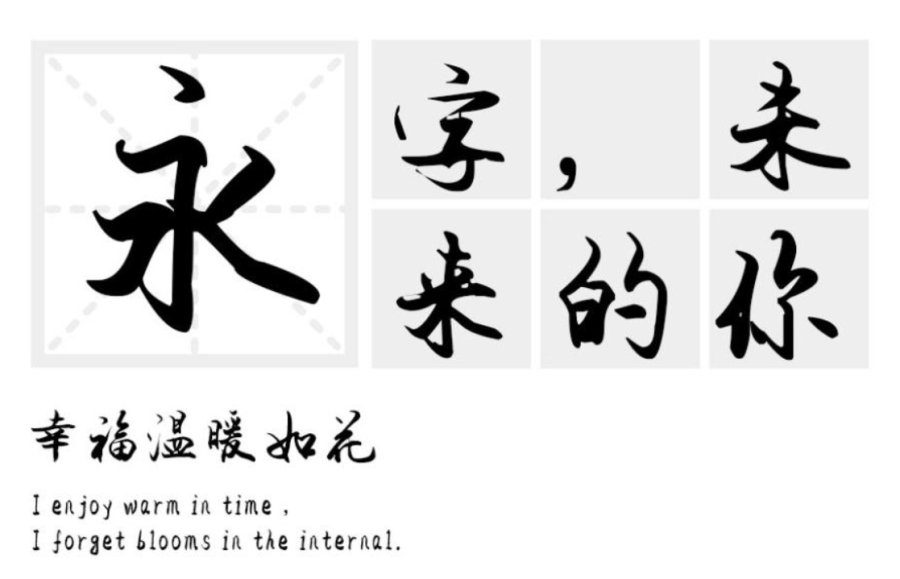
这款“汉标转运体”字体笔画流畅飞扬繁简结合,结体左紧右松,开合对比强烈,进一步强化了动感。整套字体有如一气呵成,行笔迅捷华丽,其个性浪漫洒脱,适用于现代诗歌、短文的排版,以及文化、商业类品牌的广告语设计。
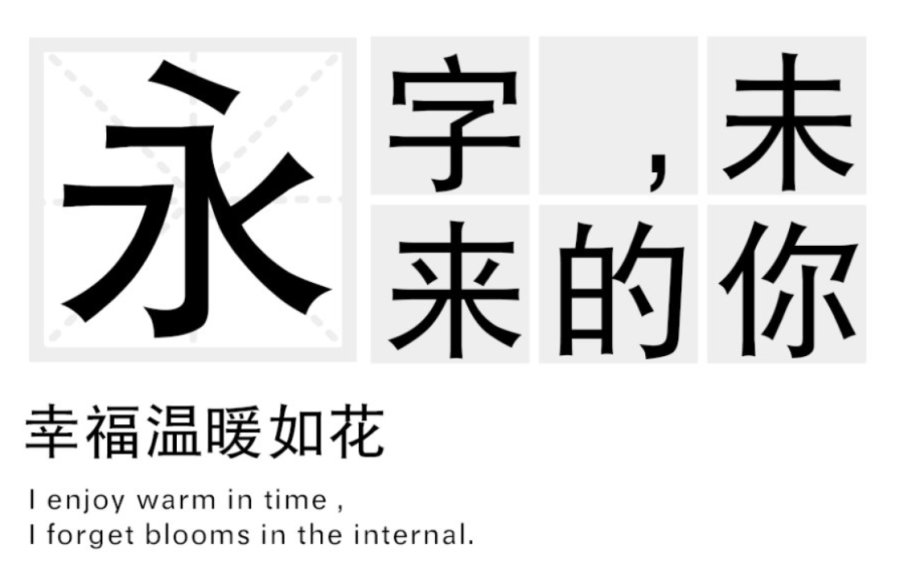
印研所黑一体:这款字体字体源于上海印刷技术研究所1962年完成的专为排印新中国首部《辞海》书眉标题设计的“黑体一号”原稿。字体结构整体方正笔形纤细,字形方中带长,笔形渗入了我国汉字传统书写味,黑白匀称,行款整齐,为了弥补因笔划纤细带来的黑体字不够端庄,在横、直笔划等的起笔和收笔部分略为加重,形似喇叭口的装饰,借以增加端庄、稳定感。
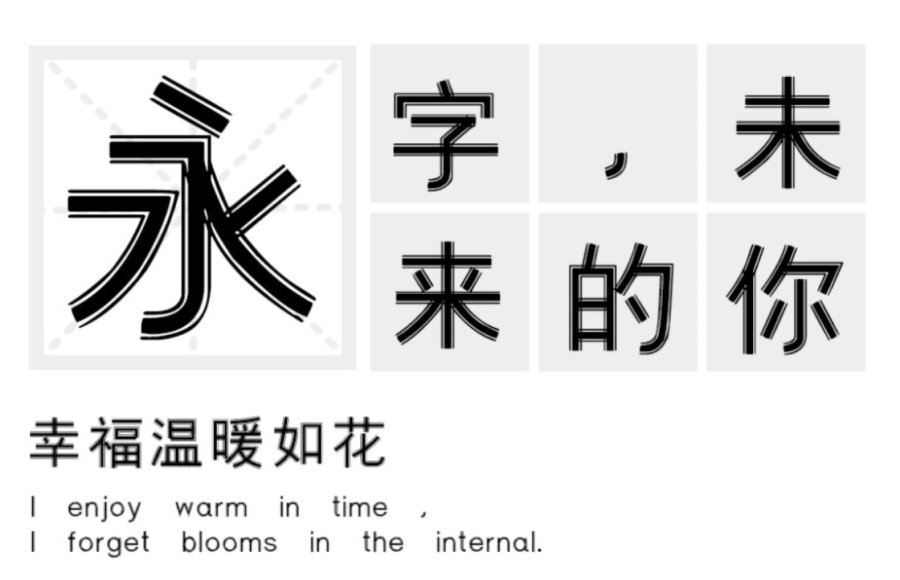
汉标外线黑体:黑字形外部加了细线,正方笔形简练,风格简静优雅;追求远距离读取功能,笔画清晰、易于识别。可标题和正文排版,尤其适合应用在空间导视、品牌形象、包装、广告等领域。